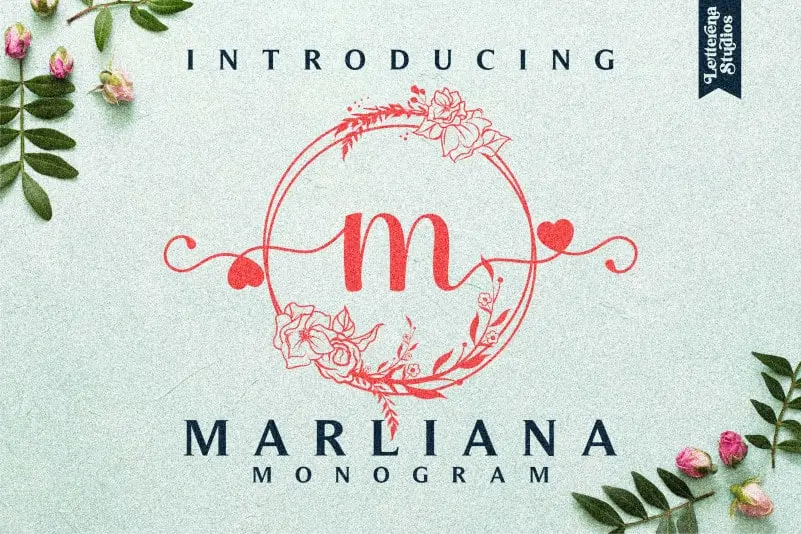
Marliana Monogram Display Font – Download Grátis
A fonte Marliana Monogram Display é uma elegante escolha para aqueles que buscam um ar sofisticado e luxuoso em seus projetos digitais. Essa font se destaca pela sua sensação autêntica, com detalhes como ornamentações de folhas de luxo que adicionam um toque exuberante aos documentos impressos. Perfeita para criar cartões de agradecimento adoravelmente delicados, postagens sociais chamativas e até mesmo logomarcas sofisticadas. Suas folhas ornamentadas também farão excelentes anexos para convites casuais ou formais para um belo jardim festa. Marliana Monogram Display é uma font incrível que transformará qualquer projeto em algo único e autêntico, combinando modernidade com classe.